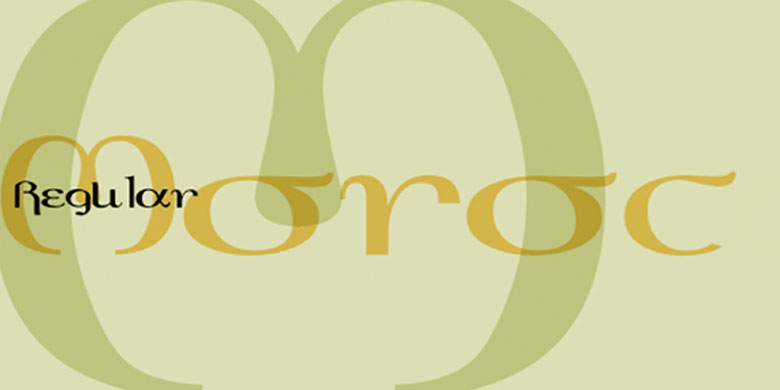
Morocco™
Morocco™,这款字体结构工整、笔画清晰,兼顾美观与易读性,适用于标题、正文、海报、包装、LOGO 等多种场景。字形优雅稳定,风格百搭耐看,适配日常排版与创意设计,让文字呈现更舒适、更具质感。Morocco™一笔一画,皆是细节,以均衡的比例、流畅的线条打造舒适视觉体验,字形端正大气,风格简约现代。无论是商业设计、品牌宣传还是日常排版,都能轻松驾驭,让文字更有格调与力量。Morocco™字体下载。
字体品牌: Linotype(Monotype) 设计师:Parson,Michael 字体分类:手写风格字体 字体属性:外文 字符集:Unicode 发布时间: 2009